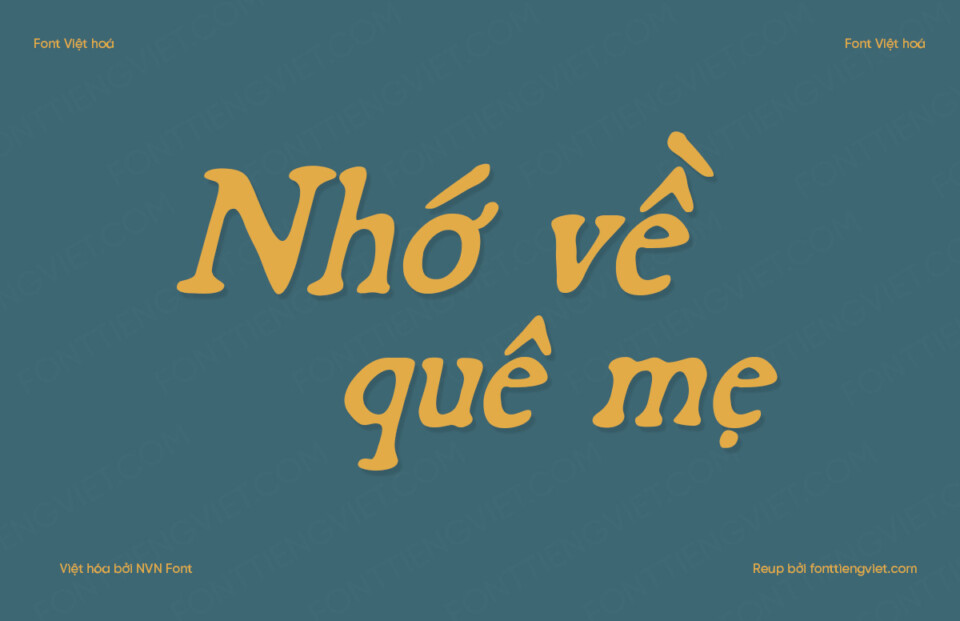
Font Việt hóa NVN Broadsheet Italic
Font Việt hóa NVN Broadsheet Italic – Serif nghiêng sang trọng cho thiết kế Editorial
Font Việt hóa NVN Broadsheet Italic là một mẫu font serif nghiêng (italic) mang cảm hứng từ phong cách chữ báo chí – tạp chí, nổi bật với nét chữ thanh lịch, độ tương phản cao và cảm giác “cao cấp” khi lên layout. Nếu bạn đang tìm một font vừa cổ điển vừa hiện đại để làm tiêu đề, trích dẫn, bìa sách hoặc poster, đây là lựa chọn rất đáng thử.
Điểm nổi bật của NVN Broadsheet Italic
• Serif nghiêng tinh tế: tạo cảm giác sang trọng, hợp thiết kế editorial, magazine, lookbook.
• Việt hóa đầy đủ: hỗ trợ dấu tiếng Việt rõ ràng, hạn chế lỗi dấu khi dàn trang.
• Dễ kết hợp: dùng tốt với font sans hiện đại để tạo tương phản (title serif + body sans).
• Ứng dụng linh hoạt: phù hợp logo chữ, branding, tiêu đề bài viết, bìa sách, banner.
Font phù hợp cho những dự án nào?
Bạn có thể dùng font Broadsheet Italic Việt hóa cho các dự án như: thiết kế bìa tạp chí, ấn phẩm in ấn, poster nghệ thuật, tiêu đề landing page, nội dung social mang phong cách thời trang, hoặc bộ nhận diện thương hiệu cao cấp. Với đặc trưng italic mềm mại, font cũng rất hợp để nhấn mạnh thông điệp, tagline hoặc các đoạn quote nổi bật.